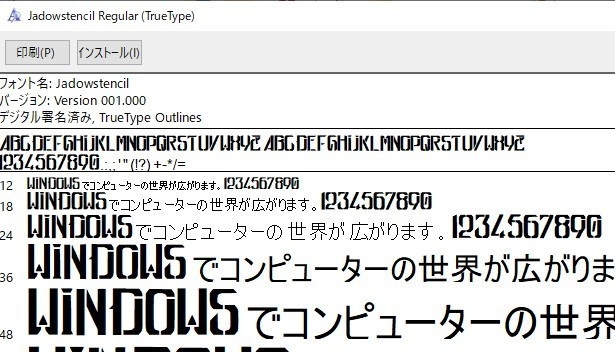
オリジナルフォント「JadowStencil」
何処か邪道にデザインされたオリジナルステンシルフォント「JadowStencil」です! サイバーパンクで独創的なデザインを意識しました! オリジナルフォント「JadowStencil」 利用規約 <デザイナ情報> ラジアン(柏木主税) misskey.numbertales-radiann.net/@RadianN_kswg/ <About Designer> Radian_kswg misskey.numbertales-radiann.net/@RadianN_kswg/ <元データ販売場所> https://radiann-kswg.booth.pm/items/5548599 <利用にあたって> 以下を合意の上、基本的に自由に使っていただいても構いません ・商業目的で利用する場合は、上記のデザイナ情報をクレジットに入れてください ・改変や再配布等もデザイナ情報のクレジット表記をしていただければご自由にご活用ください ・デザイナ「ラジアン(柏木主税)」の今後の活動に支障をきたすような利用はご遠慮ください <収録データ> 以下の文字を上記のサイトを用いりotf形式で制作しました ・英字(A~Z, 0~9) ※小文字・記号・アクセント付き文字等は収録されていません データ形式は以下の通りです ・.otfファイル <更新履歴> Ver.0.2: 2024/04/27(released:2025/09/25) ・フォントファイル再出力 ・ttf形式のフォントデータを廃止 Ver.0.1:2024/03/04 ・BOOTHでの販売開始(アルファ版リリース)